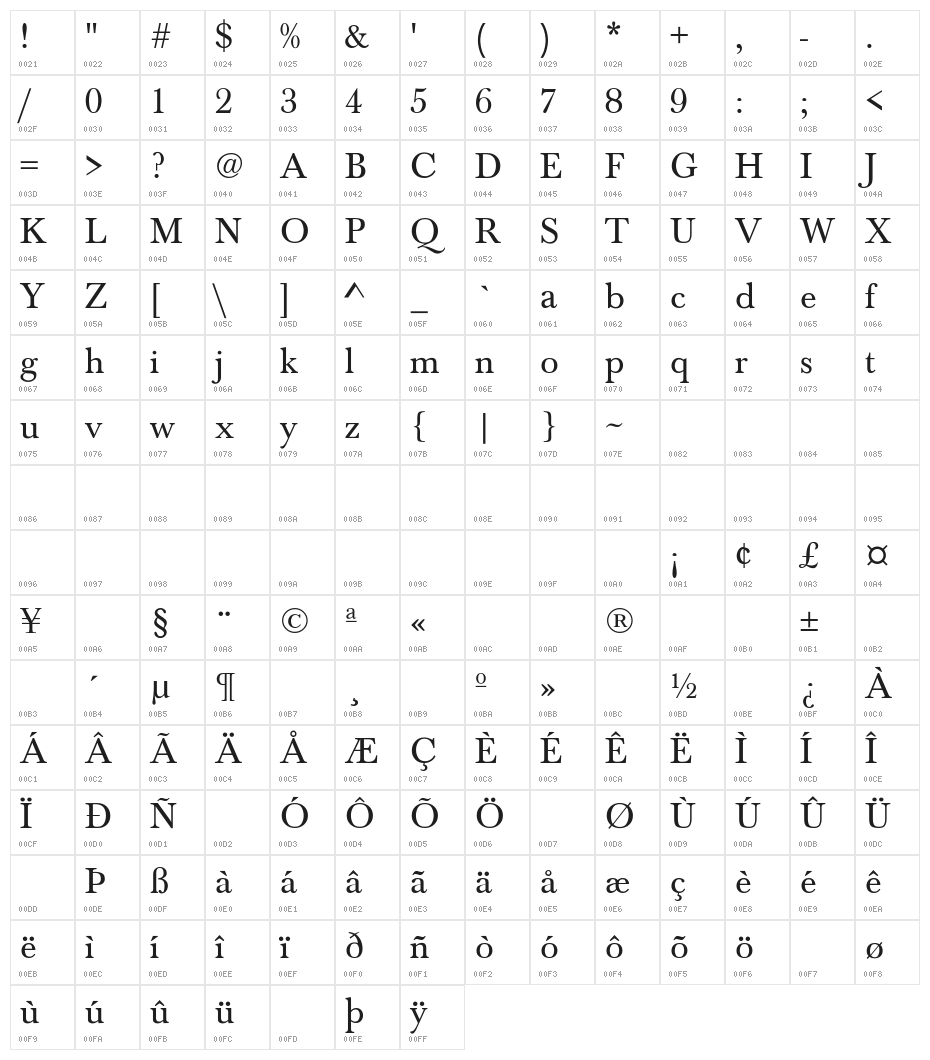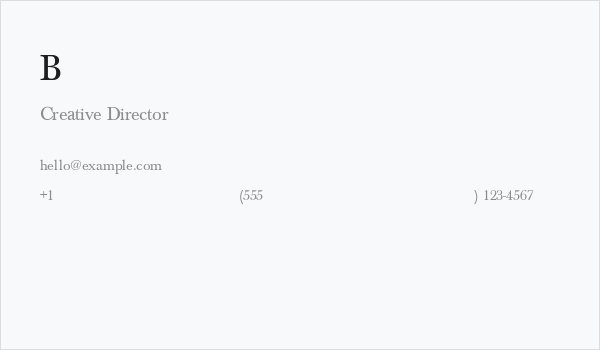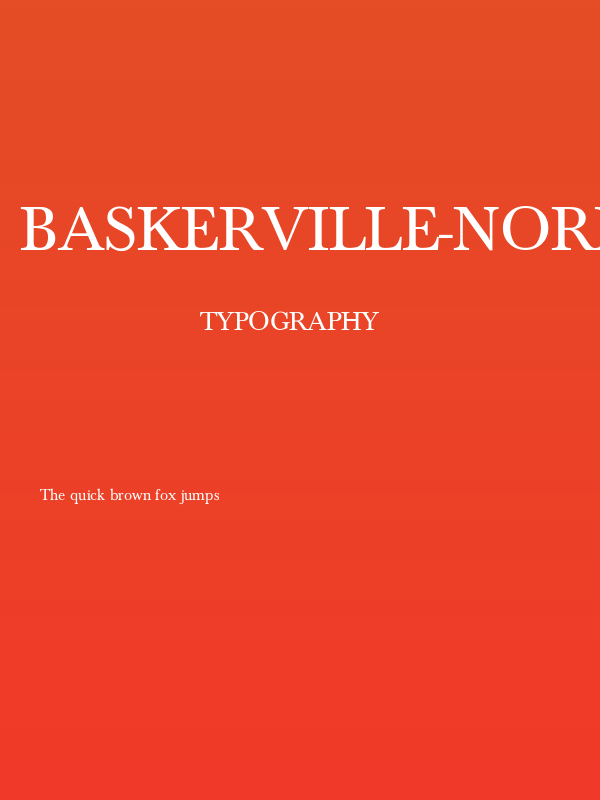
Baskerville-Normal Font
| Kategorien | Serif |
| Gesamtstil | Classic |
| Anwendungsfall | Body text, Headlines, Editorial design |
| Vorgeschlagene Projekte | Ideal for book typesetting, formal invitations, academic publications, and branding for luxury products. |